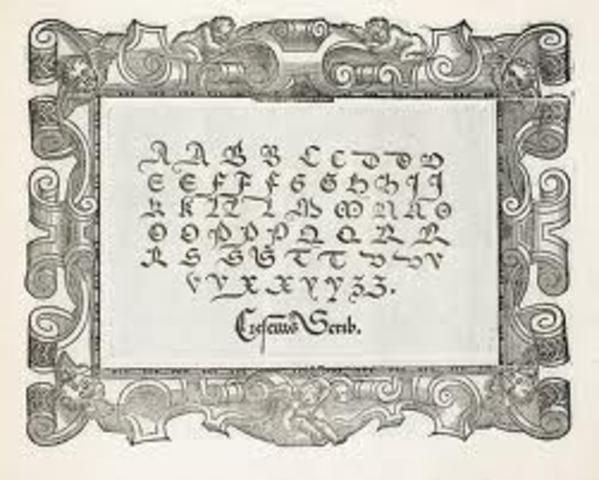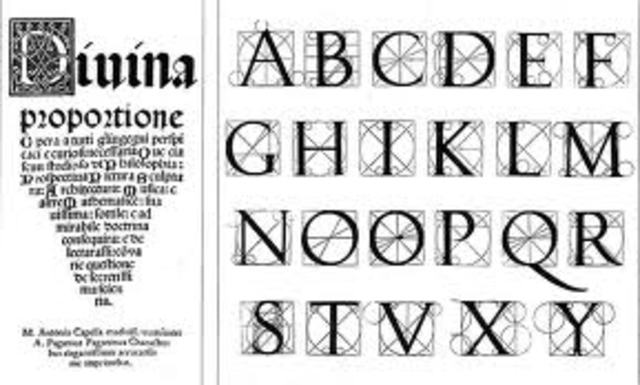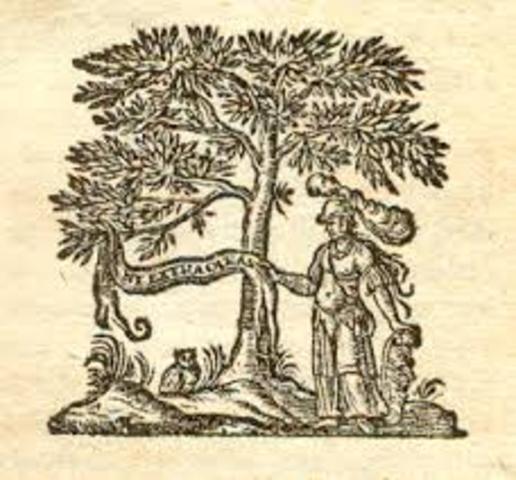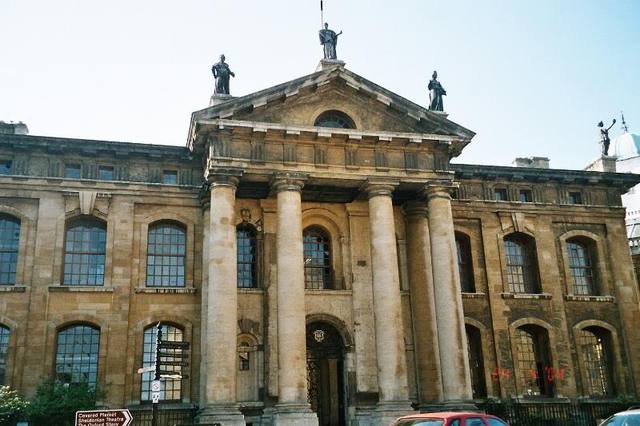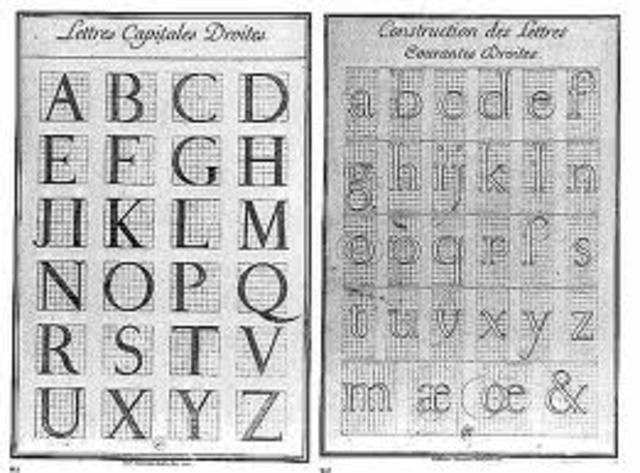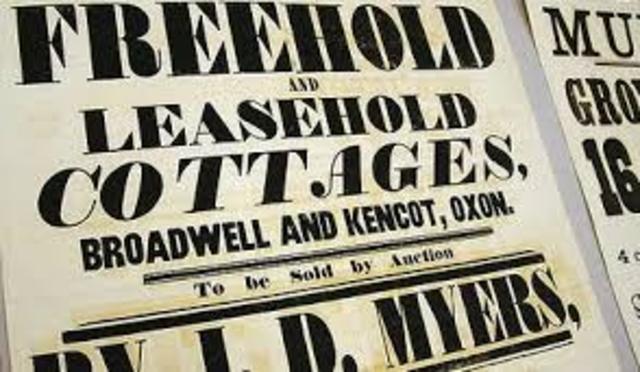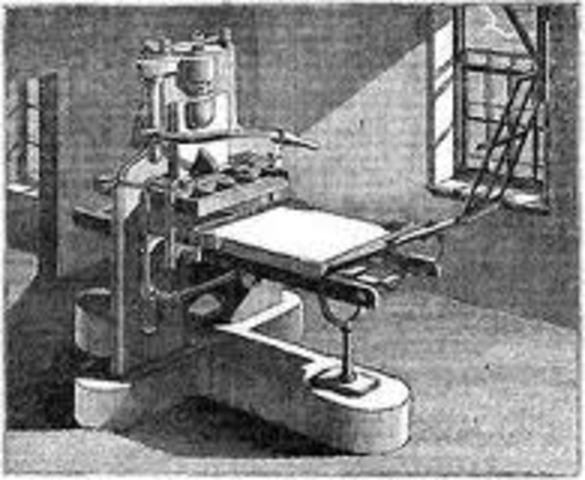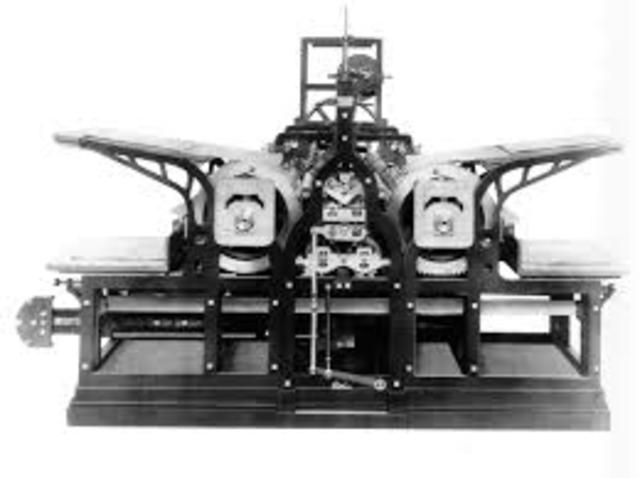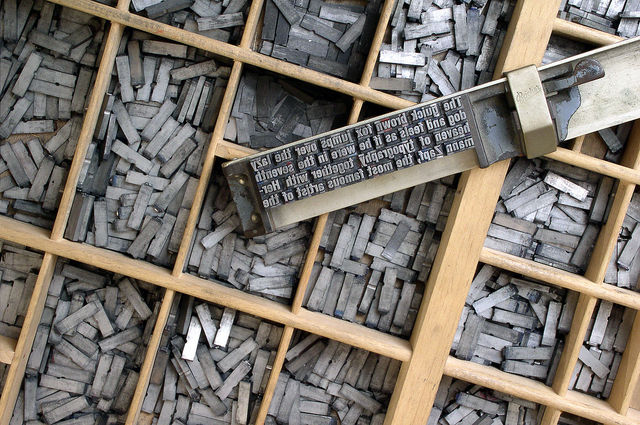
Inventa moldes para letras individuales, la obra más importante fue la Biblia de line 142
Conrad Sweynhym y Arnold Pannartz trabaja en la primera imprenta de Italia en el Monasterio de Benedicto de Subiaco, caligrafía humanistica.
Se imprimió el primer libro en inglés bajo el título de Recuyell of th Historyes of troye del Autot: Raold le Fèvre
Gullaume Le Roy introdujo la imprenta a Lyon Francia
Almus manutis fundó su imprenta Aldina en Venecia España
Ludovico Vicentino degli Arriaghi creó el primer manual de escritura e imprime el segundo
DENTRO DE LOS PERSONAJES IMPORTANTES SE DESTACAN GEOFFROY TORY CLAUDE GARAMOND, TORY FUE EL REFORMADOR DE LA LENGUA FRANCESA E INCLUYÓ EL APOSTROFE, EL ACENTO, CEDILLA LA OBRA MÁS IMPORTANTE FUE: CHAMPFLEURY
CLAUDE GARAMOND FUE EL PRIMER FUNDIDOR DE TIPOS DE TRABAJO
Antonio Vlado se convierte en el impresor papal
ANTONIO BLADO PUBLICA II PERFEXTTO SCRITTORE DE GIOVANNI FRANCECO CRECII
EL REY FELIPE II DE ESPAÑA COMISIONÓ A CHRISTOPHE PLATÍN PARA TRABAJAR EN LA BIBLIA REGIA IMPRESA EN 5 IDIOMAS, SU APORTE FUE EL USO DE GRABADOS EN LÁMINA DE COBRE PARA ILUSTRAR LOS LIBROS
EN ESTE PERIDODO SE IMPRIMIÓ FRECUENTEMENTE LA BIBLIA DEL REY JAMES Y EN ESPAÑA SE IMPRIMIÓ EL QUIJOTE DE LA MANCHA DE MIGUEL DE CERVANTES
JEAN JANSON SE ESTABLECIÓ EN PARÍS COMO IMPRESOR
APARECE EL PRIMER PERIODICO EUROPEO BAJO EL NOMBRE DE AVISA RELATIÓN ODER ZEITUG SE PUBLICA EN AMBURGO Y ESTRASBURGO
SE IMPRIME LOS PRIMEROS LIBROS DE BOLSILLO QUE HICIEERON FAMOSO A LOUIS ELVERIR
SE ESTABLECIÓ LA IMPRENTA REAL PRO ORDEN DEL REY LUIS XIII POR SUGERENCIA DE CARDENAL CHISTI Y SE COMPLETÓ EN 1642
SE ESTABLECE LA IMPRENTA EN LA UNIVERSIDAD DE OXFORD
JOHN FELL COMPRÓ PUNZONES Y MATIAS HOLANDESAS.
JOSEPTH MOXON PUBLICÓ EL LIBRO MECHANICK EXERCISES PRIMER LIBRO EN INGLÉS QUE TRATA DE LA IMPRESIÓN Y FUNDICIÓN DE TIPOS.
LUIS XIV ORDENA LA CREACIÓN DE UN COMITÉ DE ERUDITOS PARA LA CREACIÓN DE UN NUEVO TIPO PENSANDO Y CREADO BAJO PARÁMETROS CIENTÍFICOS COMITÉ LO DIRIJE JACQUES JAUGEON
INICIA EN LA CIUDAD DE PARÍS LA DINASTÍA DIDOTY SE ESTABLECE LA IMPRENTA Y LIBRERÍA
PIERRE SIMÓN ABRE SU PROPIA FUNDICIÓN Y PUBLICA EL LIBRO DE MODELOS, ESTE TRAE 4600 CARACTERES DISEÑADOS Y TALLADOS EN 6 AÑOS
PHILIPPE GRANDJEAN TERMINÓ LOS CRACTERES DEL ROMAIN DU ROI
PIERRE PUBLICA 2 VOLÚMENES DEL MANUAL TYPO GRAPHIQUE UNA EXPLICACIÓN DE SU SISTEMA DE PUNTOS
JOSEPH JACKON Y THOMAS COTTRELL EMPEZO A FUNDIR EL MODELO ARENAS TOSCAS
GIAMBATTISTA BODONI ESTABA A CARGO DE STAMPERIA REALE ERA EL IMPRESOR PRIVADO DE LA CORTE
WILHELM HAUS DE BASILEN INTRODUJO LA PRIMERA PARTES METALICAS
WILLIAN CASLON, POR ENCARGO DEL PALEOGRAFO DE OXFORD GRABÓ UN TIPO ETRUSCO SANS SERF, BASADO EN FORMA DE 2000 AÑOS DE ATIGUEDAD
FRANCOIS AMBROISE CREA EL SISTEMA DE PUNTOS QUE SE USA EN FRANCIA
SE REDISEÑÓ ÑAS FORMAS DE LAS LETRAS ROMANAS CON UN ASPECTO MÁS MATEMÁTICO, GEOMETRICO Y MECÁNICO
LORD STANHOPE DESARROLLÓ MAQUINA IMPRESORA CONSTRUIDA DE HIERRO FUNDIDO
ROBERT THORNE ALUMNO DE COTTELL EXIBIÓ POR PRIMERA VEZ LETRAS GRIEGAS
Friedrich Koenig NOS PARA UNA MAQUINA DE IMPRIMIR OPERAD A VAPOR
FRIEDRICK OBTIENE LA PATENTE ESTE INVENTO IMPRIMIR HOJAS POR HORA
THEODORE LOVE DE VINNE MANDA A REALIZAR UN TIPO EXCLUSIVO PARA LA REVISTA CENTURY ESO FUE REALIZADO POR LINN BOYD BENTON
LUIGI ORSI, EL CAPATÁZ DE BUKER VILLE TRAS SU MUERTE PUBLICA 1 VOLUMEN DE MANUALE TIPOGRAFICO
SE INVENTÓ UNA VARIANTE DEL TIPO EGIPCIO PRESENTABA PATINES CON PEQUEÑOS CORCHETES
WILLIAN THOROCUGOOD CLAREDON
LA UNITED STATES FUNDADOR ASOCIACION ESTABLECIÓ UN COMITE PARA ESTUDIAR Y FOMULAR UN SISTEMA DE PUNTOS PARA LOS FINLANDESES AMERICANOS
WILLIAN MORRIS FUNDÓ LA IMPRENTA KELMSCOTT
EN LONDRES LE ESTABLECE LA IMPRENTA ASHENDENE DIRIGIDA POR C.M.S.T JOHN HORNBY
CHARLES RICKETTS FUNDO LA IMPRENTA VALE PRESS
LA FIRMA ALEMANA BERTHOLD PUBLICA LA LLAMADA STANDAR 160 DE ESTADOS UNIDOS Y FUE EL DISCO DE 10 ESTILOS DE LETRAS SUNS FERIT
T.J. COBDEN SANDERSON Y EMERY WALTER ESTABLECIO LA PRIMERA IMPRENTA DOVES EN HAMMER SMITH
LOS PINTORES FUTURISTAS AÑADEN FRAGMENTO DE PERIODICOS Y OTROS MATERIALES IMPRENTA COLLAJES EL LIDER FILIPPO TOMMANSO MARINETTI
INTERNATIONAL TYPESETTING PRESENTÓ EL INTÉRPRETE QUE PERMITE FUNDIR LINEAS.
WILLIAN ADDISON DWWIGGINS ACUÑO EN FRASE DE DISEÑADOR GRAFICO
PIET ZWART CONTRIBUYE AL DESARROLLO DE LA TIPOGRAFIA MODERNATODO INFLUENCIADO POR EL NEOPLASTISISMO
HERBE BAYER DIRIGIO EL TALLER DE TIPOGRAFIA DE LA BAUHAUS EN SU INTENTO POR LOGRAR UN ALFABETO SIMPLIFICATIBO PROPUSO ELIMINAR LA MAYUSCULA
JOSEF ALBERT REALIZÓ UN DISEÑO DE LETRAS DE PLANTILLA
JAN TSCHICHOLD PROPUSO EL ALFABETO UNIVERSAL
LE PUBLICA EL SEPTIMO Y ULTIMO NUMERO DEL CUADERNO TIPOGRAFICO -THE HEURON RECOPILACION DE LOS VALORES TIPOGRAFICOS
SE PUBLICA EL SEPTIMO Y ULTIMO NUMERO DEL CUADERNO TIPOGRAFICO - THE HEURON RECOPILACION DE LOS VALORES TIPOGRAFICO TRADICIONALES EL STANLEY MORISON
ROBERT HUNTER MIDDLETON DISEÑO UNA PANTILLA STENCIL
LOS APORTES EUROPEOS FUE DARLE NUEVOS IMPETUS EN LA LLAMABA GANA LA PUBLICIDAD
HOGOUNET Y MOYRON INVENTARON EL FOTOCOMPONEDOR LUMITYPE - PHOTON
BRABDURY THOMPSON FUE SU ALFABETO SIMPLIFICADO - MONOALFABETICO
LE PRESENTA UN RETIRAMIENTO POSTERIOR DE LA IDEA DE ALFABETO SIMPLE LLAMADO ALFABETO 26
LA TECNICA FOTOCOMPOSICION INICA EL DESPLAZAR A LOS CARACTERES METALICOS
HERNANN ZAPT EN SU LIBRO MANUALE TYPOGRAPHICUM INDICA LOS REQUERIMIENTO DE CAMBIO
CON LOS DASAFIOS DE LA TELEVISION, HACE NECESARIO LA REINVENCION DE LA NATURALEZA DE LA TIPOGRAFIA
APARECE LA MAQUINA DE ESCRIBIR DE PELOTA DE GOLF LA SELECTRIC DE IBM, UN AMQUINA DE OFICINA CAPAZ DE CAMBIAR EL TIPO Y TAMAÑO DE LOS CARACTERES
SE LANZO EL OCR-A UN DISEÑO BURDO QUE PRODUCIA CARACTERES EN RETICULA DE CUATRO
WIN CRUEWEL CREIA QUE LA PANTALLA SERI AL FUENTE PRINCIPAL DE COMUNICACION TIPOGRAFICO DEL FUTURO COMO UN TIPO EXCLUSIVO PARA UN MEDIO - ALPHABET -NEW
SUGE INLA INTERNATIONAL TYPEFACE CORPORATION (ITL) FUNDADA POR HERB LUBALIN Y AARON BURNS, SE UNEN CON ED ROND- THALER, EL PROPOSITO ERA COMERCIALIZAR NUEVOSDISEÑOS TIPOGRAFICOS
LANZO EL PROGRAMA DE COMPU IKARUS
APARECE LA COMPUTADORA PERSONAL (PC)
MATTHEU CARTER FUNDO BITSTREAM LA PRIMERA FUNCION DGITAL
FRIEDRICH POPPL
ADOBE LANZA EL LENGUAJE POSTSCRIP
SUMNER STONE STONER SANS
CHARLES BIYOLOWY KRISTHOFER CREARON EL TIPO LUCIDA ESPECIALMENTE PARA IMPRESION LASER
CAROL TWONMBLY